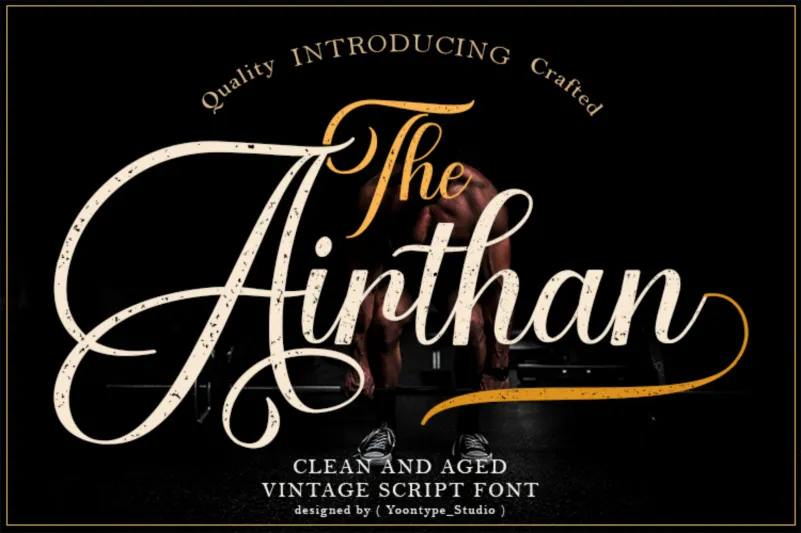
Airthan Script Font – Fonte Grátis
Airthan Script Font
A fonte ‘Airthan Script Font’ é inspirada na elegância dos traços de arte impressa tradicional. Ela se move pelo universo das artes decorativas, onde cada letra carrega consigo uma história de mãos habilidosas que desenham em papel. Desenvolvida sob a inspiração da escrita chinesa e coreana, Airthan Script incorpora um toque mágico na sua composição, como se fosse tocada por notas melodiosas do fundo. Para quem procura uma fonte para projetos que valorizam o belo e o espiritual, ‘Airthan Script Font’ é a escolha perfeita, oferecendo um toque misterioso e elegante ao seu design. Este conjunto de letras é ideal para qualquer projeto gráfico que busque dar destaque à sua criatividade com uma paleta única e fascinante.